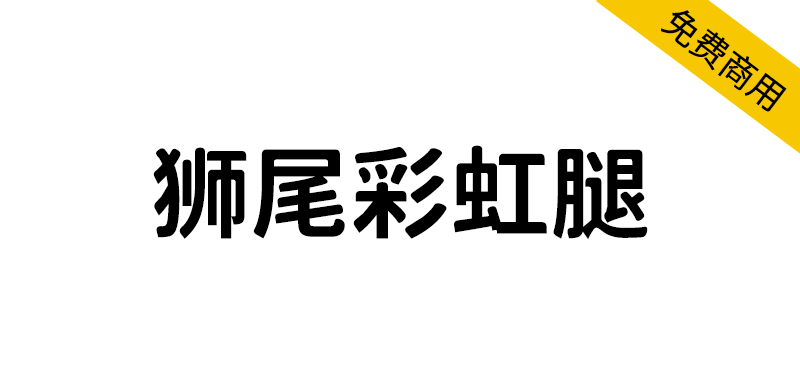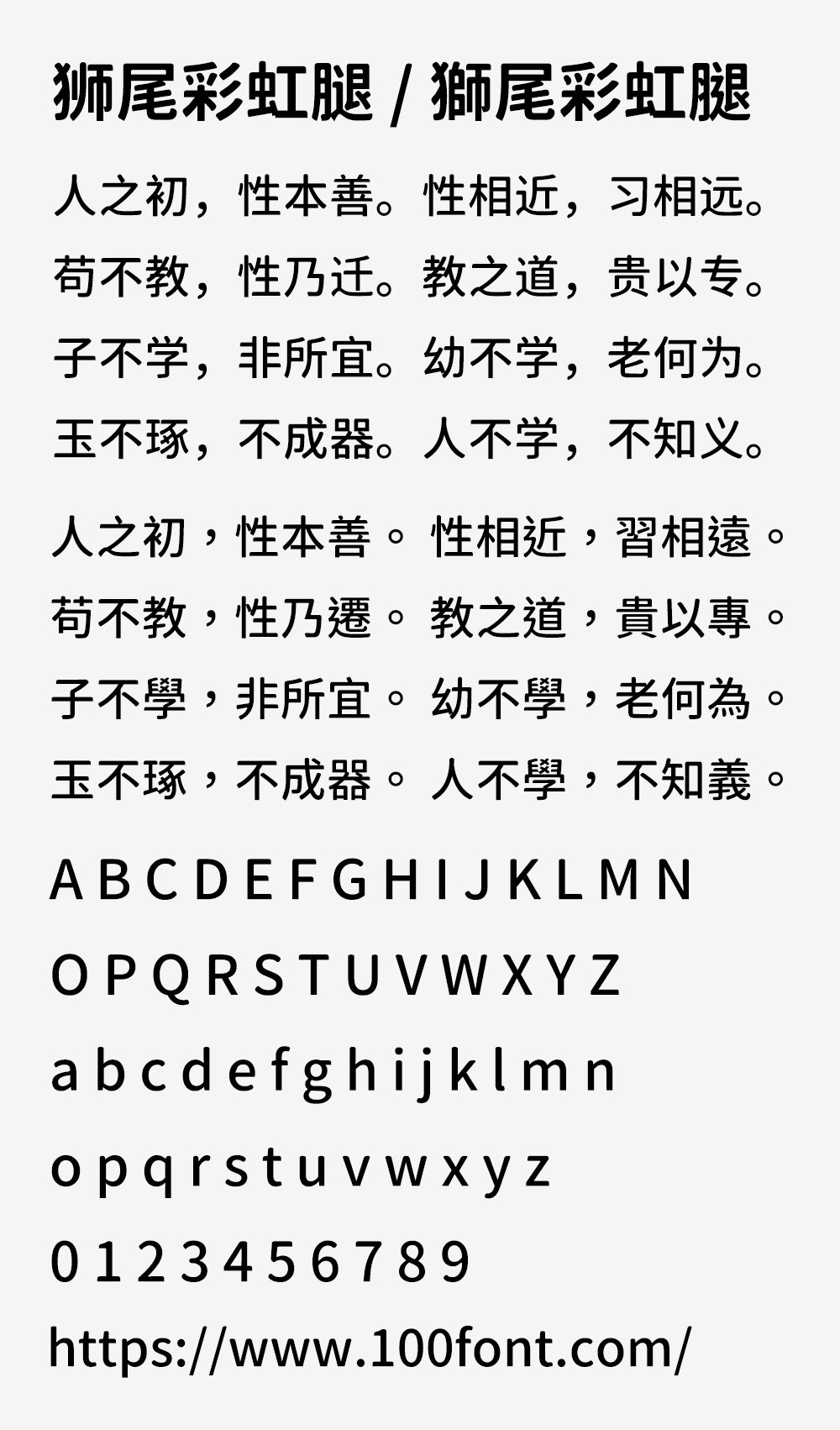
狮尾彩虹腿基于思源黑体的上半边变圆改造,更加简明现代化的字体。狮尾彩虹腿的特色是上半边圆体+下半边黑体,一个综合的字体,「口」字的上沿有一点点像彩虹形状。和思源黑体一样,有7种字重,支持简体中文、繁体中文、韩文与日文,可以免费商用,欢迎大家自由应用、自由优化、自由改作!
狮尾彩虹腿和「狮尾霓腿黑体」的主要差别在笔触是否有做调整,霓腿所套用的效果较少,在笔触没有做调整。